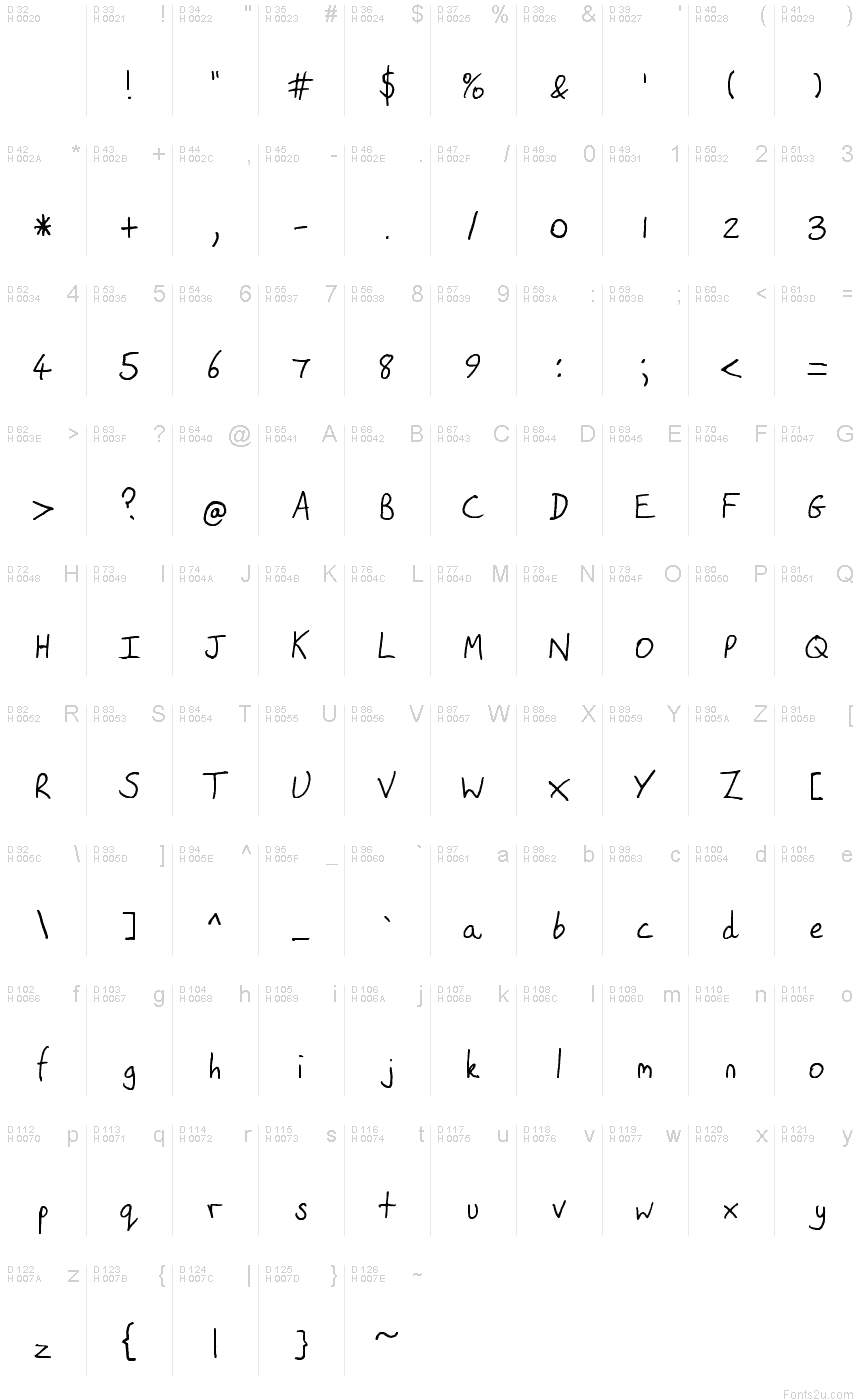
FG Amura je bezplatné ručně psané písmo od Font Garden, které díky stylu připomínajícímu psaní fixem působí uvolněně a osobně. Písmena přirozeně „kmitají“ a kombinují široké, oblé tahy s rychlými, úzkými obraty, takže výsledek připomíná spíše poznámku napsanou rukou než uhlazený font.
Je to tedy skvělá volba pro ziny, plakáty, obaly alb, kavárenské menu a balení, kde chcete dosáhnout neformálního, lidského dojmu. Hodí se také pro krátké nadpisy, titulky a citáty, protože díky nepravidelnému rytmu a o něco větším velkým písmenům dodá pár slovům na charakteru, aniž by působilo příliš strojeně.